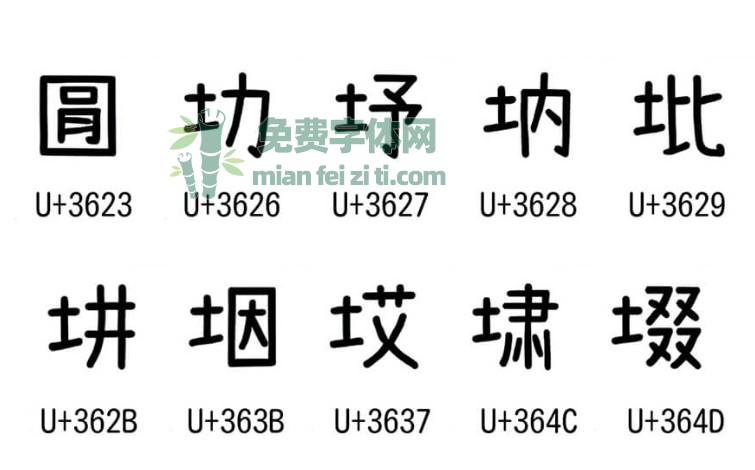
cjkFonts 全濑体是基于濑户字体透过深度学习智能造字,产生的字体数量是跟思源黑体相同,所以是全面支持繁简日韩字体,弥补了濑户字体没有的繁体及简体字,可以安心使用,不会遇上缺字的情况。
由于是电脑学习了字型的特点及风格后,每个字根据学习后的数据造字,所以字体的风格会跟濑户字体有轻微的分别。
以下是造字的过程 :
- 深度学习训练
这过程是教电脑学习字型的特点及风格,就像教小明友学写字一样。电脑要24小时不停训练,一般训练3至4天,初步字体成形。深度学习训练 - 调整字体
训练完成后,检视产生的字体,如果有变形的情况,就人手修正。 - 再训练
修正后的新字体,再加入训练,重复步骤一,让机器学习新的字型特点。 - 再训练
反复一至三的步骤,当产生的字型达到满意效果,然后就可以产生全部字型。 - 筛选及调整
产生的字体数量大约4万2千个字左右,当中会有一些字是变形的,要筛选出来再人工调整,这个步骤工作量是非常大及花费大量时间的。 - 输出字体档案
使用软件组合字体,然后输出字体档案(ttf)。
造出一款字大约要用3至4个月时间,如果人手充足的话,可以缩短至2个月。
濑户字体的数量已足够应付一般情况,为何要基于它再造字?
濑户字体是一款很可爱的手写字,在繁体支援上是很足够的,但是在简体字上,缺字情况严重,很多日常会使用到的字也缺少(图.1 显示简体部分缺字),我们希望可以补回缺少的简体字,令到繁体及简体的应用上也可以使用此字体。
本款“cjkfonts_全濑体”是一款书写很新颖的字体,字体大方,适合各种设计作品使用!欢迎下载!